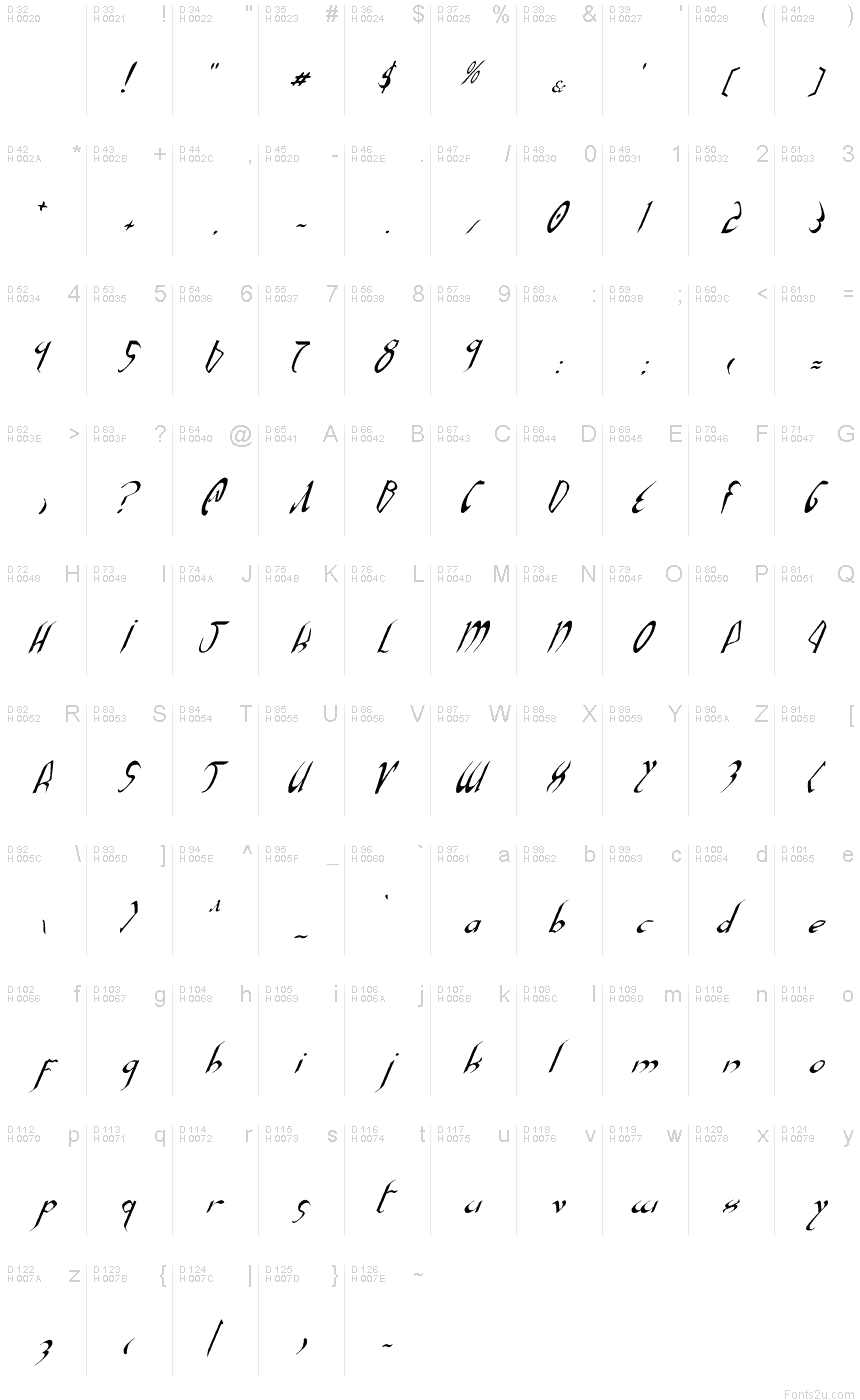
Podgląd czcionki Xaphan Italic
Xaphan Italic od Iconian Fonts to darmowy, pochyły krój gotycki o ostrym charakterze blackletter. Litery mocno się pochylają i przechodzą w długie, haczykowate pociągnięcia, łącząc ostrza niczym klingi z kilkoma bardziej obłymi kształtami, co nadaje całości dynamiczny, mroczny i nieco ceremonialny wyraz.
Świetnie sprawdzi się na plakatach, okładkach albumów, w tytułach gier, w brandingu fantasy czy krótkich nagłówkach, gdzie darmowy font ma budować dramaturgię bez zbędnych dekoracji. Wykorzystaj go w planszach tytułowych, zapowiedziach czy inicjałach w stylu monogramu, gdy chcesz postawić na cięty, średniowieczny dynamizm.